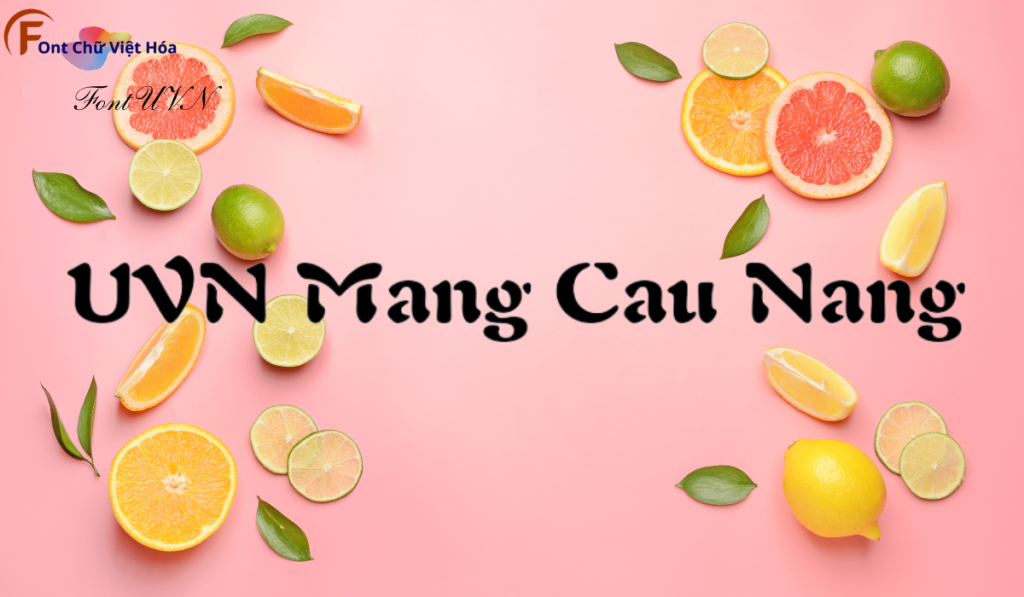
Font UVN Mãng Cầu Nắng Việt Hóa
Tác giả: UVN Mãng Cầu Nắng Việt Hóa
Bộ Font: UVN
Kiểu chữ: Kiểu chữ có chân
Độ dày: Thường
Font UVN Mãng Cầu Nắng Việt Hóa là một font chữ không chân hiện đại, thuộc bộ font UVN. Được thiết kế với mục tiêu mang lại sự tinh tế và thanh lịch, font này phù hợp cho các dự án thiết kế như website, tài liệu, và bao bì sản phẩm. Với các nét chữ rõ ràng và độ dày đều đặn, Font UVN Mãng Cầu Nắng Việt Hóa không chỉ dễ đọc mà còn tạo cảm giác chuyên nghiệp. Việc Việt hóa font giúp người dùng dễ dàng sử dụng trong các thiết kế tiếng Việt, mang lại sự tiện lợi và thẩm mỹ cao.